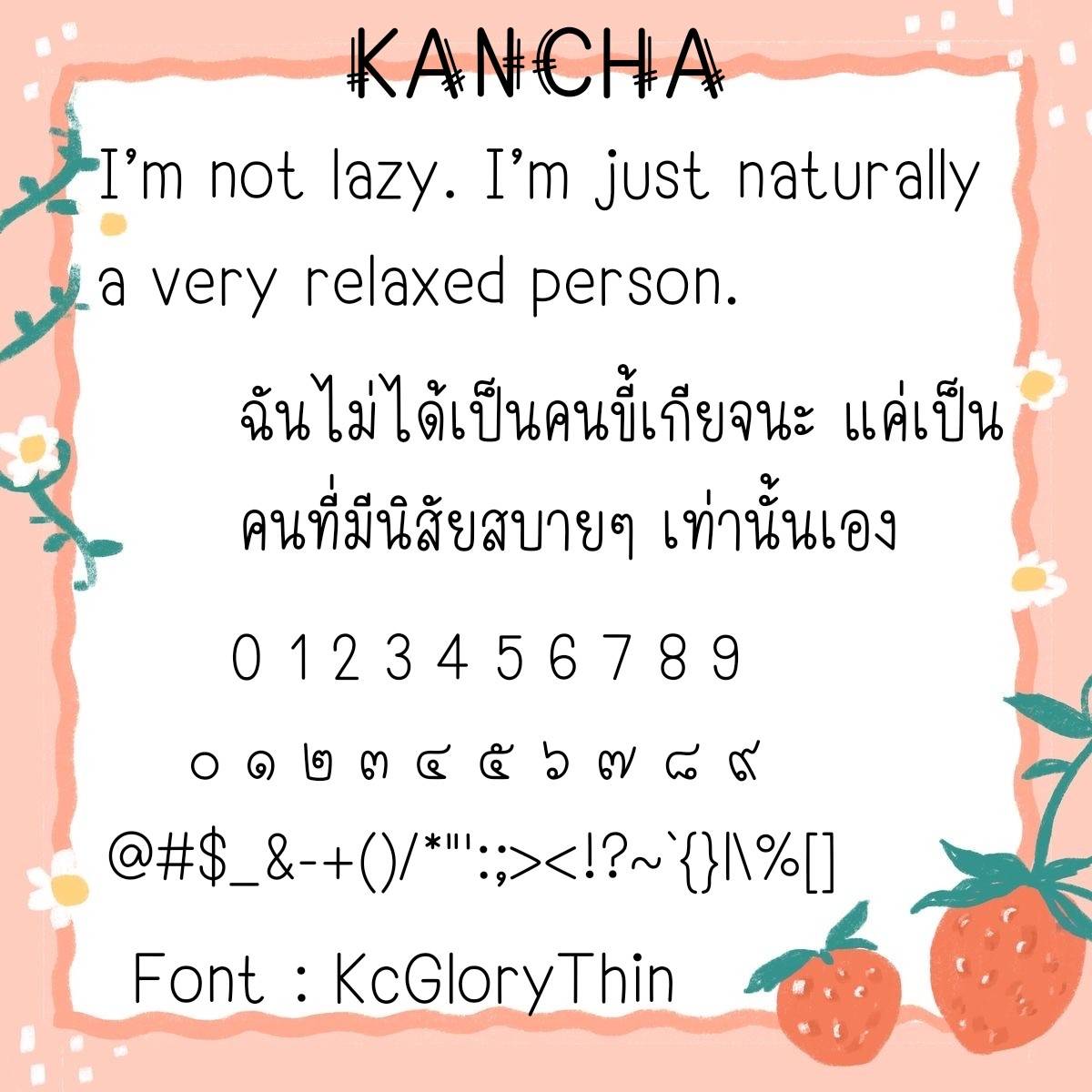
Font KcGlory
ชื่อสินค้า : Font KcGlory 💙
🔸ฟอนต์สไตล์วัยรุ่น ตัวผอม แต่ยังอ่านออกง่าย และมีลูกเล่นเป็นตัวพรีเมียมให้ด้วยค่ะ🥰💙
🔹Teen-style font, slim but still easy to read. and has features as a premium for me🥰💙